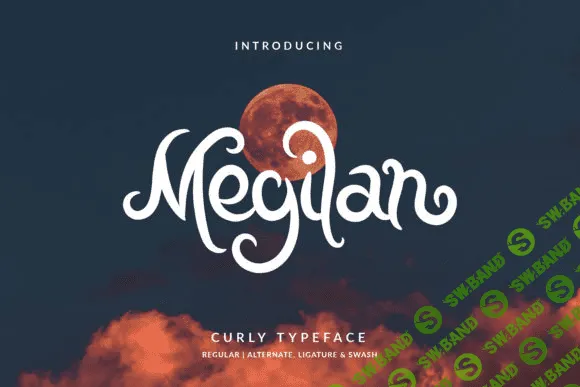
Название: Megilan Font
[Creativefabrica] Megilan Font
Мегилан - это уникальный и интересный рукописный шрифт.
Невероятно универсальный, этот шрифт впишется в широкий спектр дизайнерских решений.